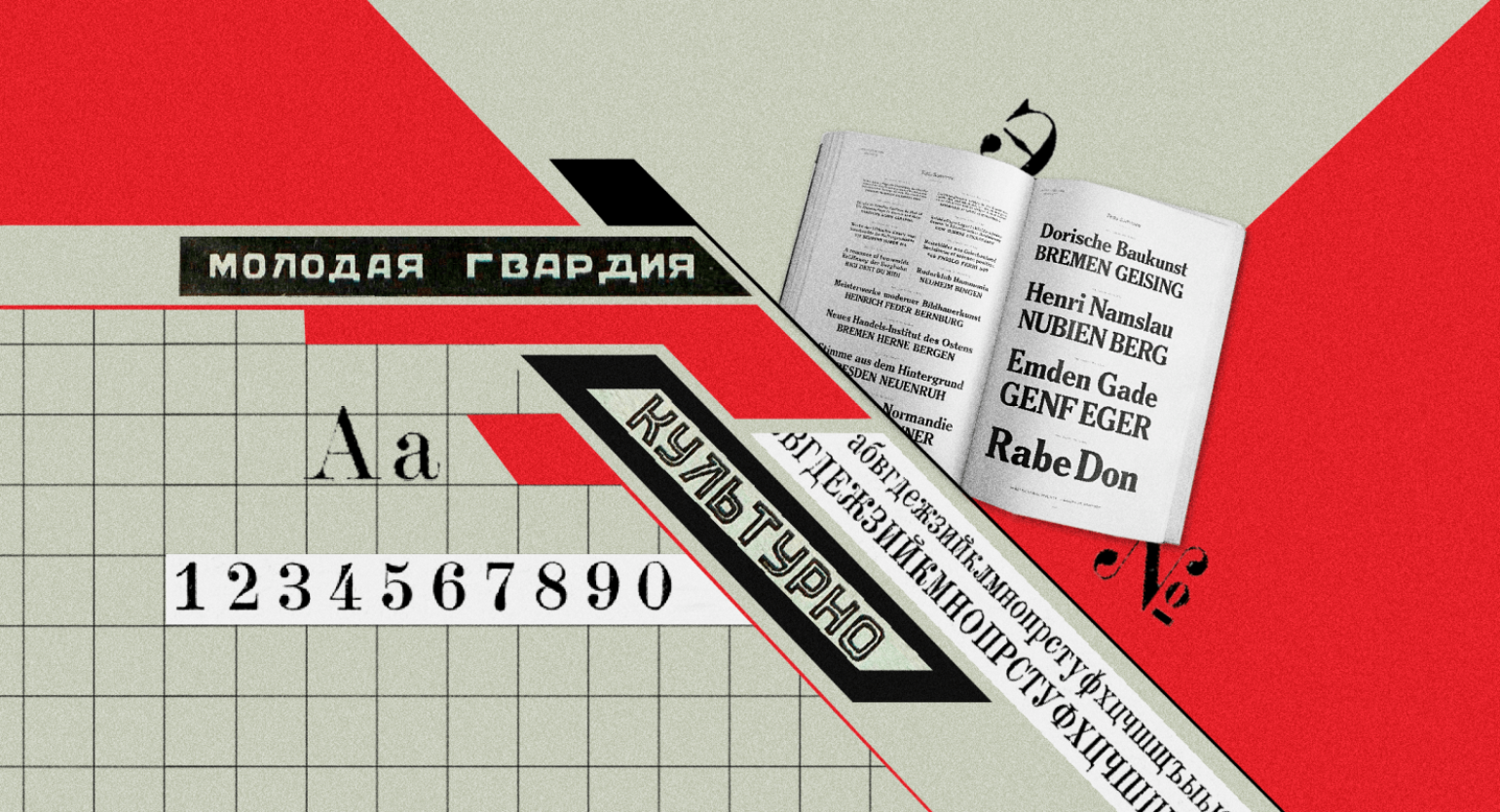
Серп и кегль: шрифты СССР
Рассказываем, какие гарнитуры вошли в советский стандарт и как их использовали.
Несмотря на кажущееся разнообразие советских шрифтов, которыми оформляли обложки книг, вывески магазинов и уличные афиши, полиграфия в СССР существовала в строгих рамках. В 1930 году Всесоюзный комитет по стандартизации принял обязательный Общесоюзный стандарт 1337 «Шрифты гартовые», он устанавливал единый список допустимых гарнитур.
Прежде всего в базу стандарта отбирали шрифты, пригодные для многотиражных изданий книг, газет и детской литературы. Невошедшие гарнитуры — «большое количество случайных, неудобочитаемых и антихудожественных модернистских образцов» — изымали из типографий и отправляли на переплавку.
В ОСТ 1337 вошёл 31 шрифт, за каждым закрепили порядковый номер и название. Шрифты объединили в семь серий, пять из них использовали для текстов: обыкновенные, латинские, «Коринна», академические и елизаветинские.
Из нашего материала вы узнаете про главные шрифты Советского Союза, которые до сих пор легко найти в букинистических книгах и на плакатах того времени:
Обыкновенные гарнитуры
Самой распространённой гарнитурой стандарта был «Обыкновенный шрифт», его создали на Шрифтолитейном заводе в словолитне Лемана в Санкт-Петербурге. В нём было семь начертаний: обыкновенный простой, обыкновенный плотный, учебный, курсив обыкновенный, альдине полужирный прямой, курсив и жирный.
Эта серия отличается от других вытянутыми символами, большой контрастностью переходов от тонких к толстым линиям. Верхние и нижние основания подчёркнуты линиями, при этом утолщения у закруглённых букв строго вертикальные.
Обыкновенным простым и обыкновенным плотным (в кеглях до 12 пунктов) набирали газетные тексты. Обыкновенный курсив использовали для небольших подзаголовков, заметок и выделений в тексте. Более крупными кеглями — 12 и 16 пунктов — выделяли статьи и заметки, а прописными буквами набирали заголовки и подзаголовки.
Альдине полужирным прямым и курсивом в мелких кеглях выделяли важную информацию, а в крупных их также иногда использовали для заголовков. Жирный редко применяли в газетной печати, он считался книжным шрифтом.
Создатели стандарта предполагали, что шрифты этой серии пробудут в нём недолго — до их замены новыми, но по факту они входили в ГОСТ до конца существования СССР.
Графика обыкновенного шрифта. Наиболее типичные буквы серии обыкновенного шрифта
Для набора учебников, букварей и пособий для начальных школ использовали «Гарнитуру №3 Учебную». Её частично составили на основе бывших гарнитур №6 и №11 словолитни Лемана и Флинша. Позднее эту гарнитуру упразднили как самостоятельную единицу, и она стала частью «Обыкновенной гарнитуры».
В июне 2020 года энтузиасты создали гарнитуру DXOldStandardStudium — цифровую версию «Гарнитуры №3 Учебной». Для реконструкции использовали образцы шрифта 16 кегля из каталога словолитни Лемана и «Каталога ручных и машинных шрифтов». DXOldStandardStudium выпущен в двух версиях: с сохранением исторического рисунка и доработанный с изменённой графикой.
Шрифт DXOldStandard Studium — цифровая версия металлического шрифта «Гарнитура №3 Учебная» по ОСТ 1337
Латинские гарнитуры
Латинскую гарнитуру разработал академик и немецкий криптолог Петер Шнорр для словолитни Бертгольда в 1899 году. Кириллический вариант он создал в 1901 году.
Латинская гарнитура включала четыре шрифта: светлый, курсив, полужирный, курсив полужирный. Она широко применялась для набора газетных заголовков, шапок и подзаголовков.
Русский художник Николай Пискарёв отмечал достоинства курсивного начертания, но был недоволен жирным. Он предлагал создать более строгие жирные шрифты для титульного набора и для всех начертаний нарезать 24-й кегль.
Для группы этих шрифтов характерны меньшая контрастность между основными и добавочными линиями, основания букв в форме остроугольных треугольников и утолщения закруглённых букв в наклоне. Набранные латинской гарнитурой заголовки имеют спокойный и однотонный вид, поэтому после введения в стандарт она стала очень распространённой, её использовали в более чем половине всех вышедших книг.
Мелкие кегли латинского светлого шрифта от 6 до 10 пунктов чаще применялись в качестве книжного шрифта, а остальными выделяли лозунги, цитаты и рубрики. Крупные кегли от 12 пунктов применяли для набора газетных заголовков.
Графика латинского шрифта. Наиболее типичные буквы латинской серии
Медиевальные, или эльзевировские гарнитуры
К шрифтам этой группы относятся: коринна светлая и коринна полужирная, академический светлый, светлый курсив и полужирный.